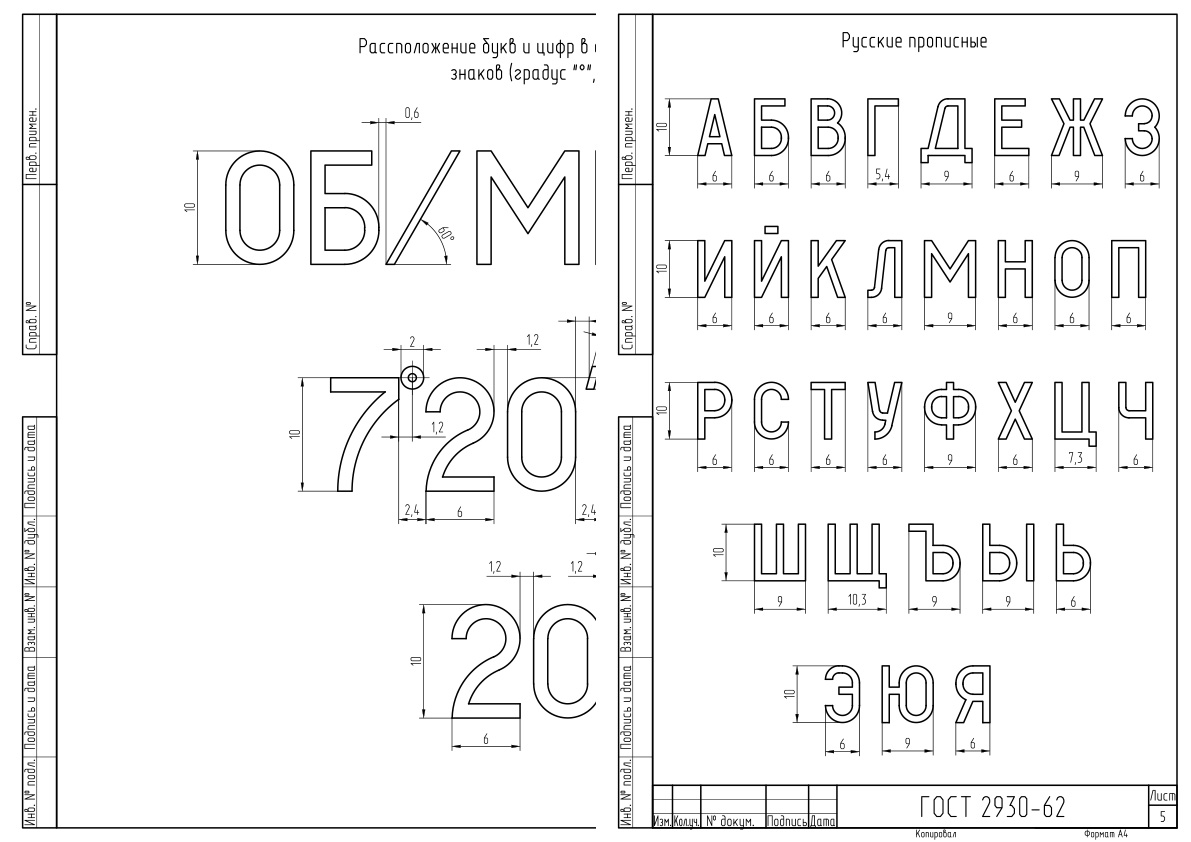
Чертежи шрифта по ГОСТ 2930-62, применяемого для маркировки циферблатов и другие детали измерительных приборов. Состав:
ПО - Шрифт прописной основной (ПО (русский, латинский, греческий, цифры арабские)
С - шрифт строчной (русский и латинский)
ЦР - шрифт цифр римских
М - знаки математические
Нумерация листов соответствует нумерации страниц ГОСТа.
Шрифт ГОСТ 2930-62